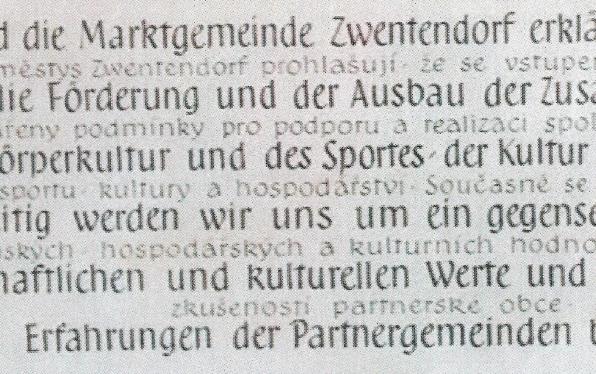
Mein erster Eindruck: Das ist kompetent mit der Hand geschrieben und dann reproduziert, nicht gesetzt (erkennbar daran, dass häufige Buchstaben leichte Formunterscheide aufweisen).
Edit: Digital käme das hier in die Nähe: